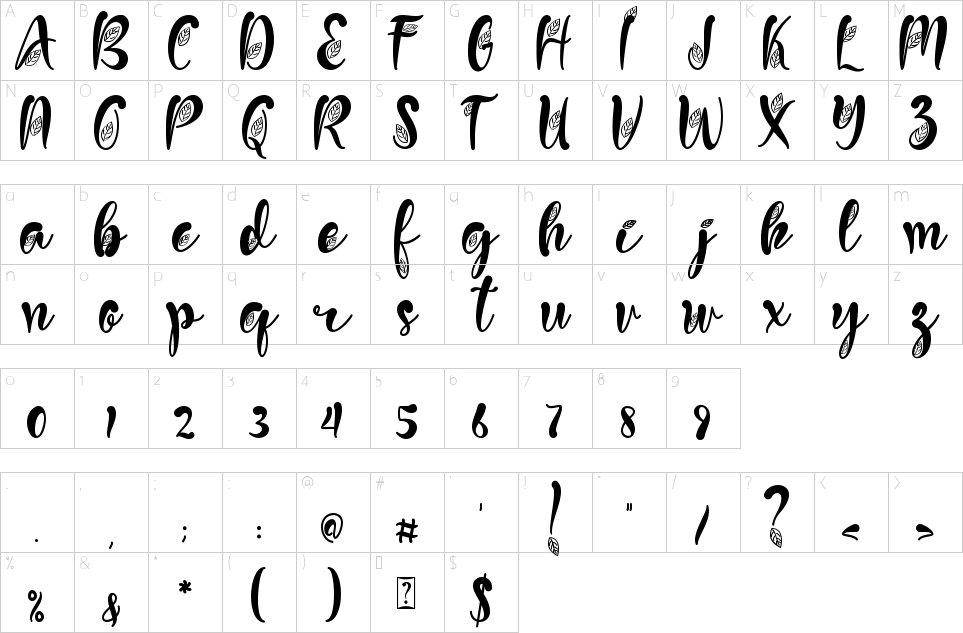
Aqui está uma versão curta e envolvente para a descrição do download da font ‘Green Love Font’, seguindo as instruções: A font Green Love é uma escolha perfeita para quem procura expressar amor de forma natural e elegante, tanto no design gráfico quanto nas aplicações digitais. Desenvolvida por Yoga Letter, essa font foi projetada com um toque de verde que faz referência à sustentabilidade e ao cuidado pelo planeta. Com seu design limpo e harmonioso, ela combina perfeitamente em ambientes onde a delicadeza e a simplicidade são valorizadas. O Green Love Font é ideal para criações que exigem uma tipografia delicada sem deixar de ser eficaz, tornando-o uma excelente escolha não só para designers gráficos, mas também para desenvolvedores de aplicações digitais. Oferecida gratuitamente, essa font foi baixada mais de 4 mil vezes e acredita-se que sua beleza e versatilidade possam impressionar ainda mais o seu público. Esta descrição transmite as características principais da font, destacando seus benefícios estéticos sem entrar em detalhes técnicos ou específicos do design. Ela é informada e convidativa, ideal para uma página de download.